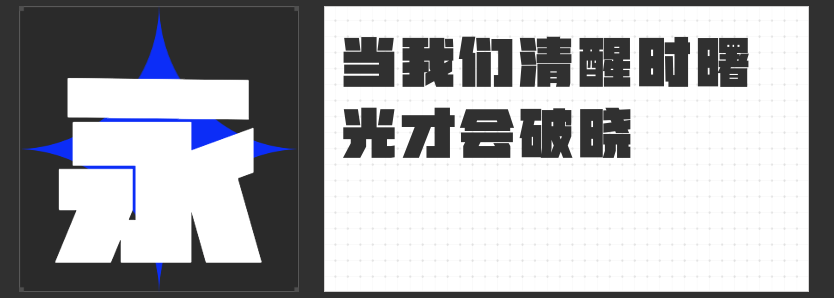
力量美学新范式:四款极具视觉张力的设计字体推荐
在当代视觉设计中,力量感不仅是视觉语言的表达,更是一种情绪的传递。以下四款字体以独特的结构设计与笔触处理,构建出极具冲击力的视觉场域,为品牌标识、海报标题、产品包装等场景注入硬核美学基因。
一、励字开拓者简 超黑
以极简主义为内核,励字开拓者简 超黑通过纯粹的直线构建字体骨架。其方正字型与适中重心奠定稳定基调,中宫舒展确保小字号下的识别性。笔画横平竖直,棱角如刀刻般分明,起笔收笔的平切处理强化机械感,内部几何空间均匀分布,形成视觉平衡的精密系统。去钩化设计弱化传统黑体的动态感,而撇捺点的竖直化处理则创造出镜像对称的视觉奇观,适合科技、工业、建筑等需要理性表达的设计场景。
二、励字暴风简 超级黑
突破传统黑体的静态框架,励字暴风简 超级黑以梯形笔画重构视觉秩序。横竖笔画粗细不均,形成动态的张力对比,撇捺点融入更多梯形元素,赋予字体向前冲的势能。这种不规则感并非杂乱,而是通过现代黑体骨架的创意延伸,构建出具有未来感的视觉语言。其略带开放性的字型结构,既保留黑体的简洁性,又通过笔触的粗粝质感传递出叛逆与突破的精神,适合运动、潮流、音乐等领域的视觉表达。
三、励字铁拳简 超级黑
如其名所示,励字铁拳简 超级黑以“力量”为设计原点。笔画粗壮如钢筋,字面宽大占据视觉中心,饱满的块面感与折角圆润处理形成刚柔并济的矛盾美学。这种设计不仅强化了视觉冲击力,更通过块面的叠加与留白,营造出如铁拳出击般的动态轨迹。其超黑字重与极简结构,使字体在远距离仍能保持高辨识度,适合需要强调存在感的标题、LOGO或广告语设计。
四、高手兵克坚黑体
作为一款无弧度创意超粗黑体,高手兵克坚黑体以“减法”诠释力量。笔画粗细统一至极限,消除所有曲线元素,仅通过直线与折角的组合构建字形。这种极致的简化非但没有削弱视觉张力,反而通过超黑字重的压迫感与几何结构的纯粹性,形成一种“以静制动”的美学力量。其设计语言直指核心,适合需要突出品牌名称或关键信息的场景,如电商标题、产品包装或品牌主视觉。
这四款字体从不同维度诠释了力量感的设计哲学。设计师可根据品牌调性,选择或组合使用这些字体,在视觉层面构建具有穿透力的表达体系。